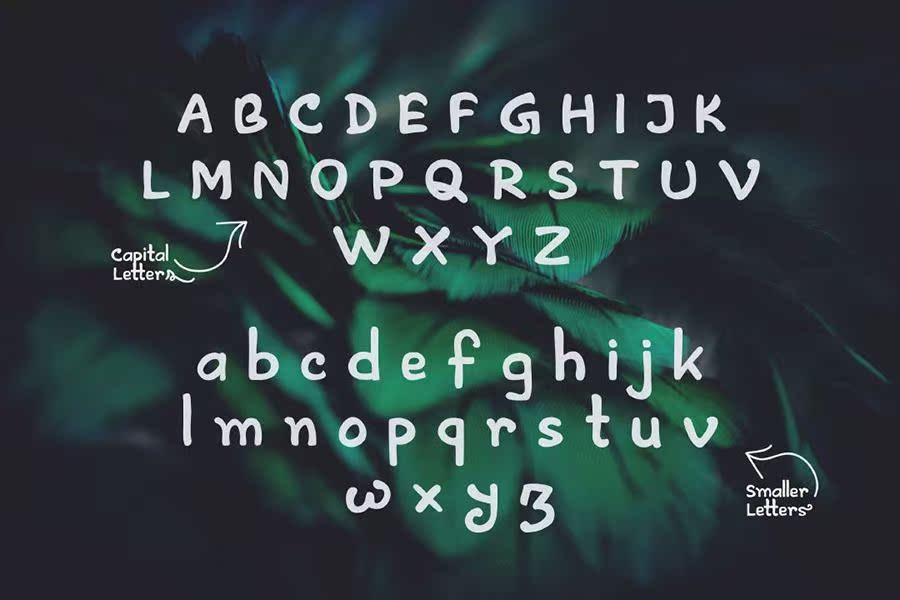
ArtlesshandWrittenFont是一种漂亮的手写、粗体、现代外观的手写字体。共有246个字形:A-Z、A-Z、0-9、多语言字符、货币符号、标点符号、替代符号等。用激情创建,从纸张到数字屏幕再到可安装的FontFile。完整版本有OpenType、TrueType和WoffWebFontFile。